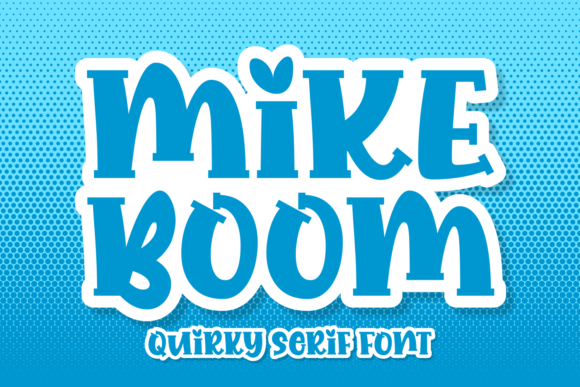
Mike Boom Font
Mike Boom Font – خط إبداعي حديث بتصميم مميز
اكتشف Mike Boom Font، الخط العصري الذي يجمع بين الجرأة والإبداع، ليضفي لمسة احترافية على تصاميمك. يتميز هذا الخط بأسلوبه الجريء وحوافه الناعمة، مما يجعله مثاليًا لاستخدامه في الشعارات، والتصميمات الإعلانية، والعناوين الجذابة، وتصميمات السوشيال ميديا.
???? المميزات:
✔️ تصميم أنيق وعصري
✔️ يدعم الأحرف الكبيرة والصغيرة
اجعل تصاميمك تنبض بالحياة مع Mike Boom Font، الخيار الأمثل للمبدعين الذين يبحثون عن التميز! ????✨